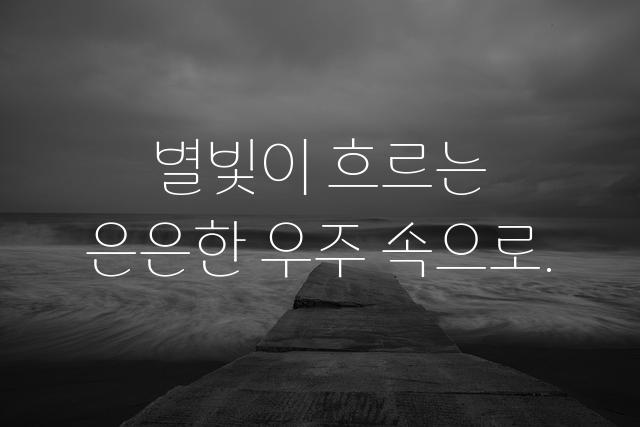
태백체는 태백시가 제작한 기본 고딕 폰트로, 제목용으로 탁월하게 사용됩니다. 깔끔하고 현대적인 느낌을 주며, 다양한 디자인에 잘 어울립니다.
태백체은(는)
기본 고딕, 감성적인, 부드러움, 길고/크고 계열의 생김새를 가지고 있으며
웹/앱 디자인, 출판 디자인, 출판물 제목 등에서 자주 활용되며, 효과적인 메시지 전달에 적합합니다.
이 폰트는 출판/미디어, 문화/예술, 이벤트/웨딩 분야에 잘 어울리며,
전통적, 편안한, 클래식한 느낌을 담고 있는 것이 특징입니다.